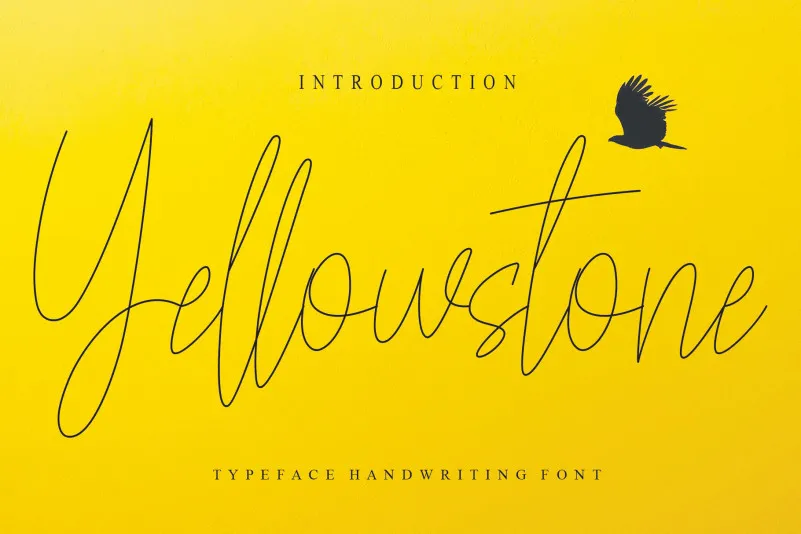
Yellowstone Handwritten Font – Fonte Grátis
Yellowstone Handwritten Font
Esta fonte “Yellowstone Handwritten” oferece um toque autêntico e envolvente aos seus designs digitais. Inspirada no estilo elegante das escritas manuscritas, ela convida você a explorar uma experiência única, repleta de detalhes cuidadosamente criados pela designer creativeletter. Com traços finos e linhas suaves, essa fonte transmite um sentimento de sofisticação e elegância que vai destacar qualquer projeto em que seja usada. É perfeita para designers gráficos que buscam uma maneira diferenciada de incorporar elementos artísticos aos seus trabalhos.